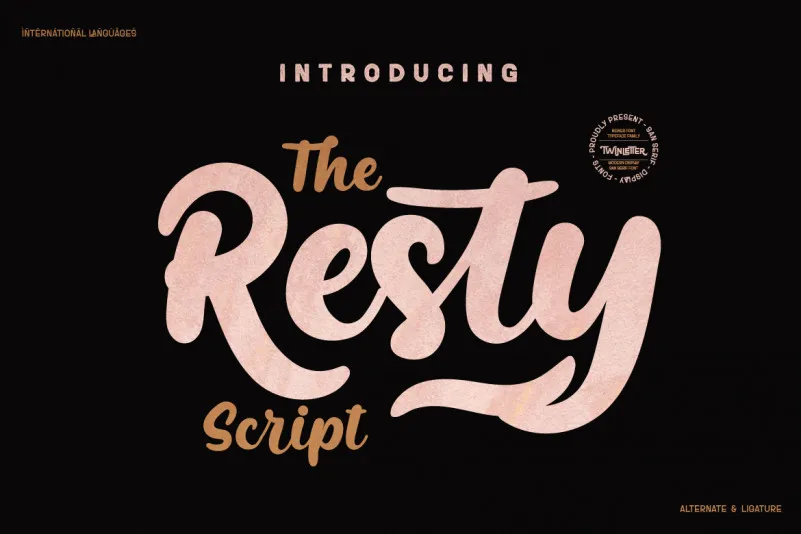
Resty Font – Fonte Grátis
Resty Font
Esta é uma fonte script bold que se destaca pela sua personalidade única e presença forte. Ideal para criar mensagens impactantes, essa fonte foi cuidadosamente projetada com a delicadeza de um traço humanoilhado, resultando em composições e partes adequadas às suas necessidades. Twinletter, o criador desta fonte script, soube capturar tanto a expressividade do estilo humanoilhado quanto seu caráter robusto para criar uma opção perfeita para designers que buscam um estilo elegante e forte. Seja em projetos de marketing, gráficos de websites ou qualquer aplicação digital que precise de um texto profundo e envolvente, esta fonte script é o elemento perfeito para alcançar seu objetivo.